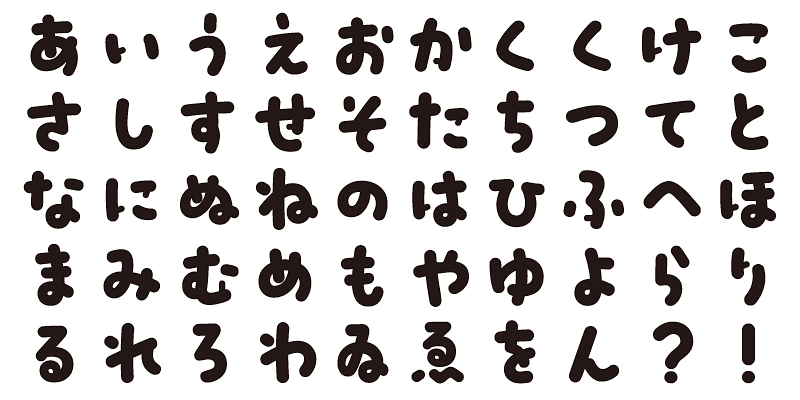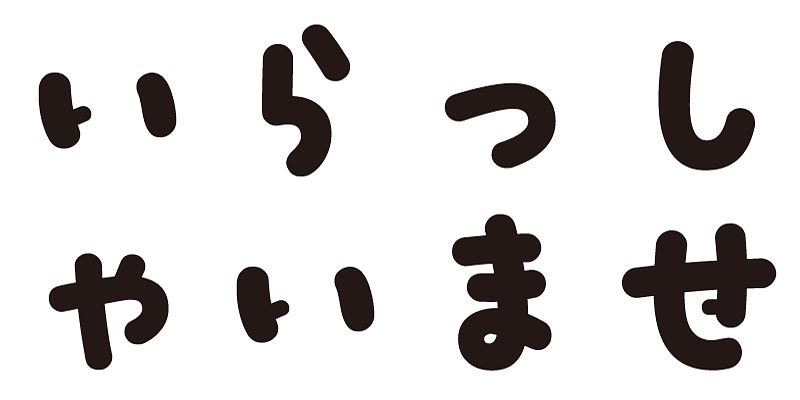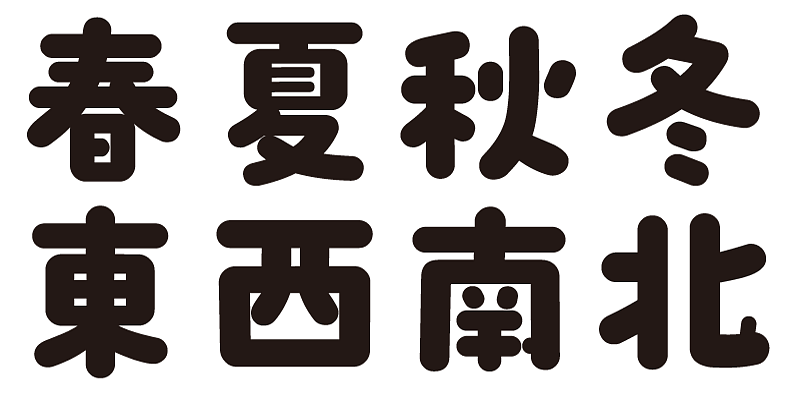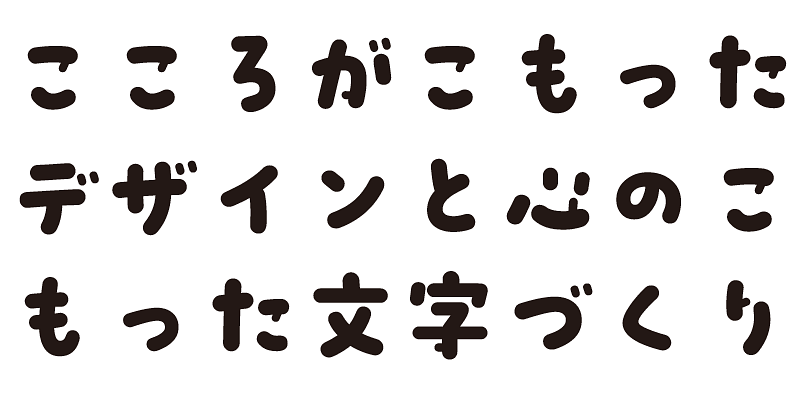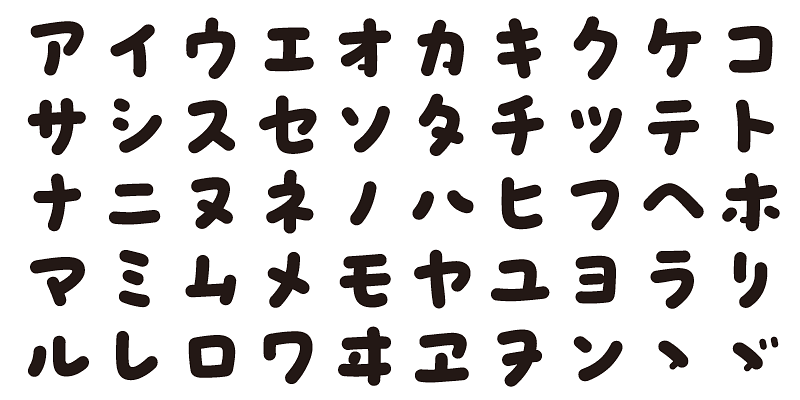
Une police de style gothique (sans empattement) ronde, douce mais dynamique.
Chaque police de cette famille de polices comprend 1 000 caractères kanji, ainsi que des caractères hiragana, katakana, alphanumériques et des signes de ponctuation.
Nous concevons des polices dans l’espoir qu’elles ajouteront une signification sous-jacente aux mots exprimés. Nous souhaitons que l’utilisateur se sente bien et qu’il éprouve du confort et de la joie lorsqu’il utilise ces polices.